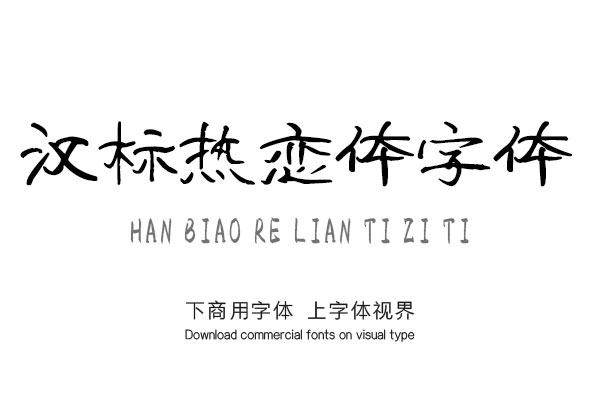
引《凤求凰一琴歌》一日不见兮,思之如狂。
设计简洁而富有特色的笔画运转、间架结构严谨有度,但我们在设计时丢掉了传统而古板文化韵味;体现弯头钢笔与白纸碰撞出来的线条火花,灵活运笔之间完美呈现热恋之间的默契。使字的魂牵梦萦道出每个情侣恋爱过程中热烈而难分的阶段,最终实现开花结果。热恋体即将开启美好的每一天。
这款字体巧妙地利用了钢笔特质,用不同倾角的笔画呈现出不同粗细,形成一种节奏感。其风格简约雅致,适用于现代诗歌、短文的排版,以及文化、商业类品牌的广告语设计。